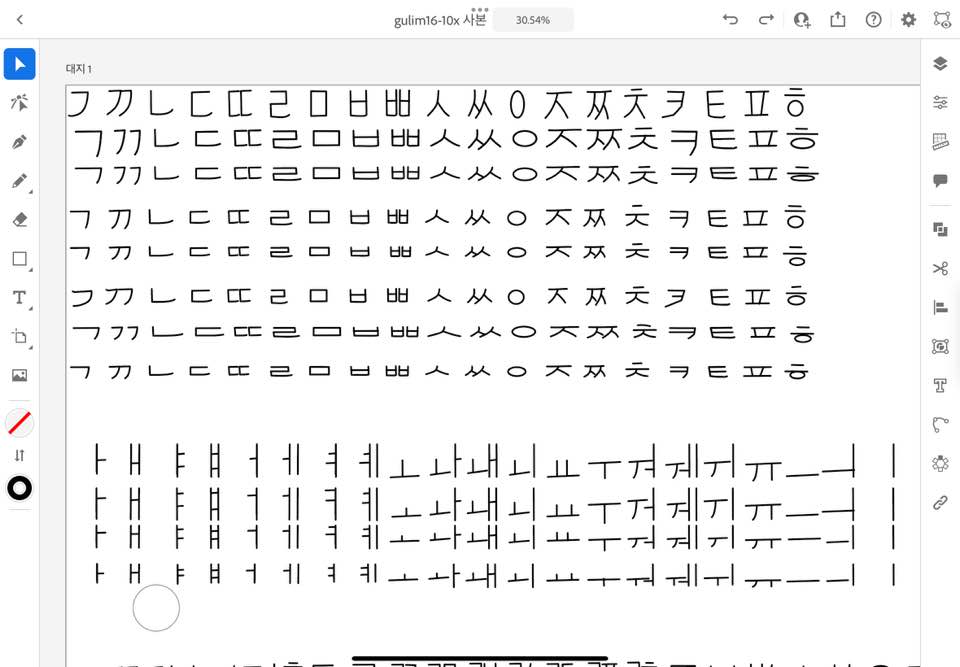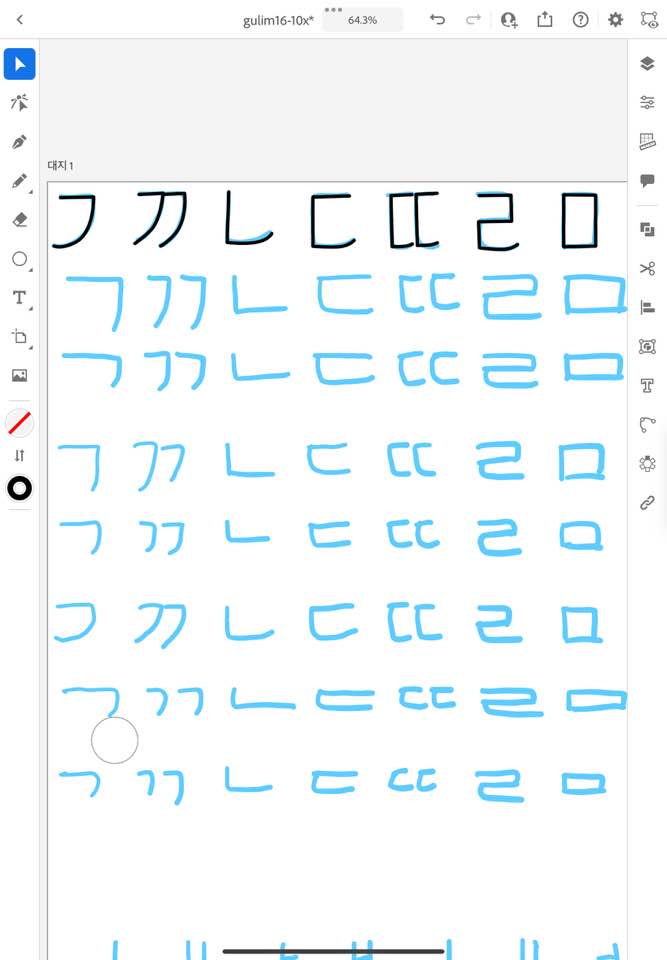
한글 폰트 생성을 위한 svg 조합형폰트 만들기4
대략 손으로 만든 손글씨로 만든 폰트를 다른 쓸모를 만들기 위해 플로터용 폰트를 만들어 보기로 했습니다.
레이저 각인용, 플로터 굴림체는 하나의 스트로크로 만들어 진 것만 레이저로 커팅을 하거나 각인을 하거나 라인별로 스트로크를 한 라인으로 작업이 되어야 숙제나 반성문을 플로터로 찍어낼 수 있습니다. 응?!?​
폰트는 stroke 로 그리고 다시 그 스트로크를 셰이프로 만들어야만 보이지만 플로터에서는 그렇게 처리하면 텍스트를 따라 몇회를 지나가게 됩니다. 그래서 두가지 형태로 제작도 가능하고 온라인에서 웹기반 한글 오토마타 입력기 및 SVG 편집기를 만들어서 SVG폰트로 결과물이 나오게 할 생각입니다.
자 이제 다시 영문폰트를 한글폰트화 하는 프로젝트를 먼저 몇개 하고 폰트 스타일 몇가지 구분하면 쉽게 폰트를 만들 수 있는 서비스와 전자책 뷰어를 만들어볼까 합니다.
내 글씨로 보는 내가 쓴 글...